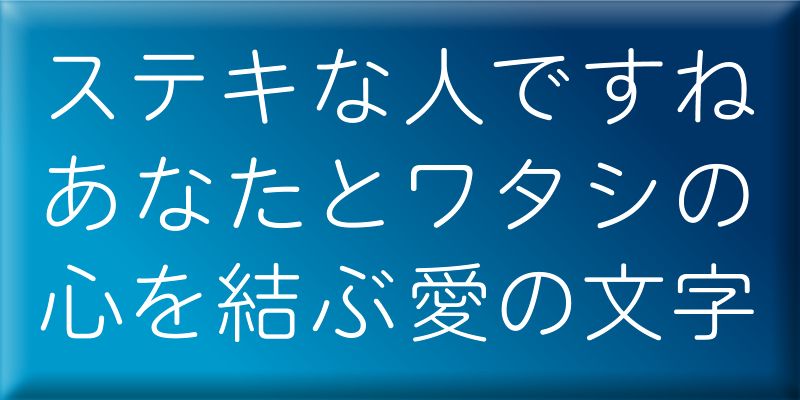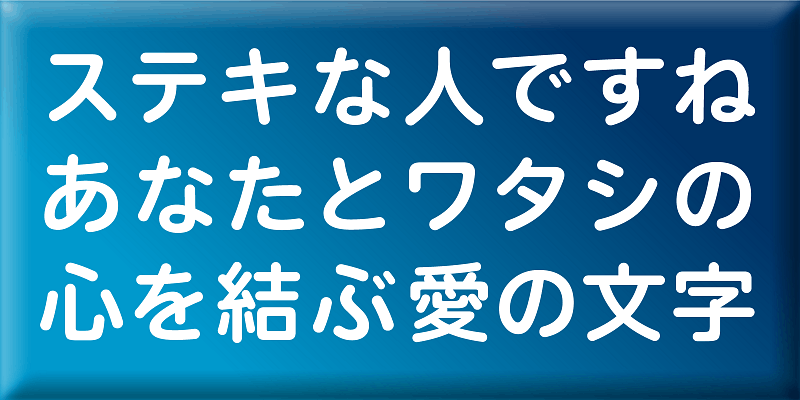
Dies ist eine einfache, sauber gestaltete, abgerundete gotische Schrift. Ihr unaufdringliches und dennoch weiches Erscheinungsbild kann Ihnen helfen, Ihre Worte richtig zu vermitteln.